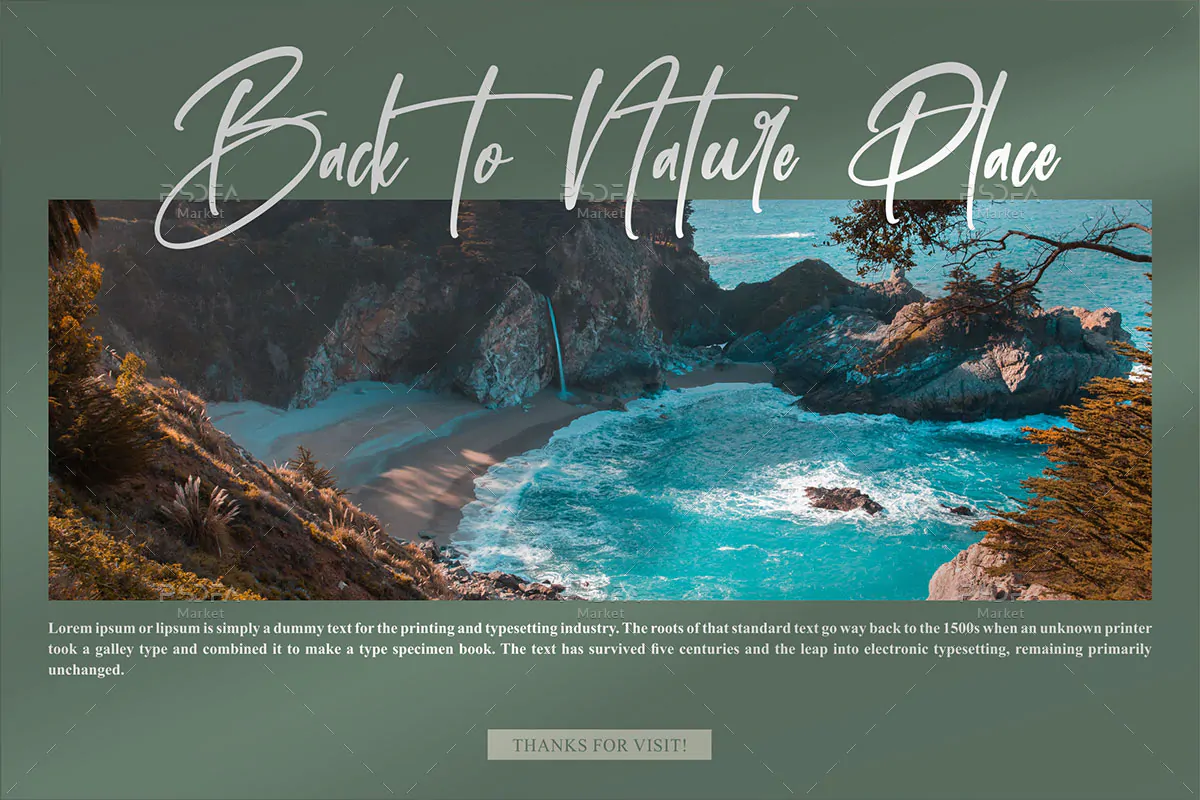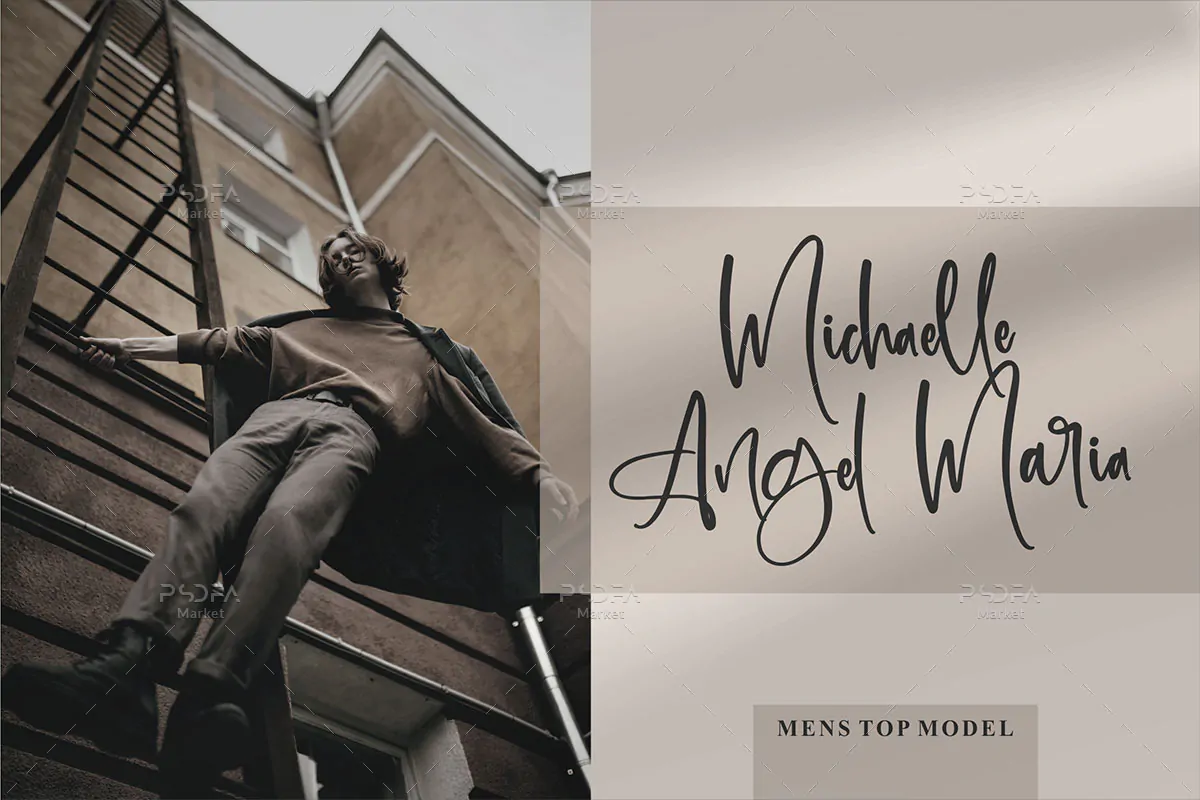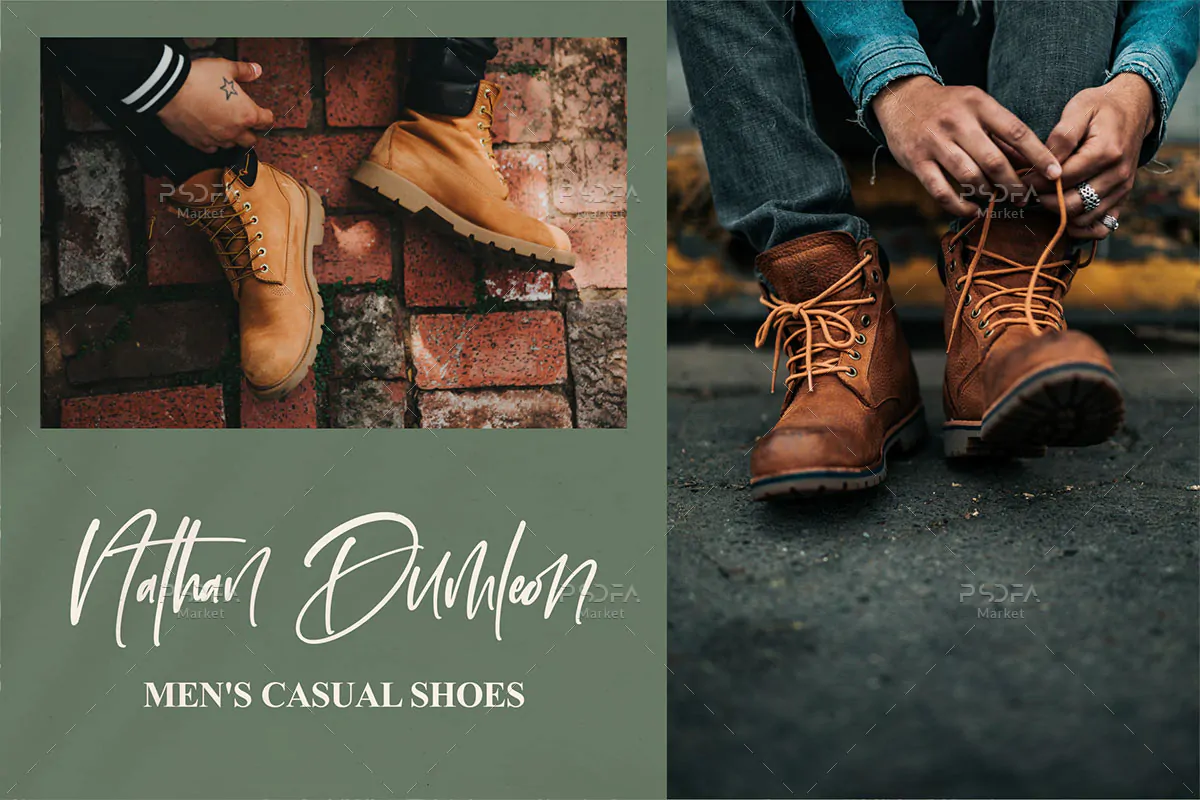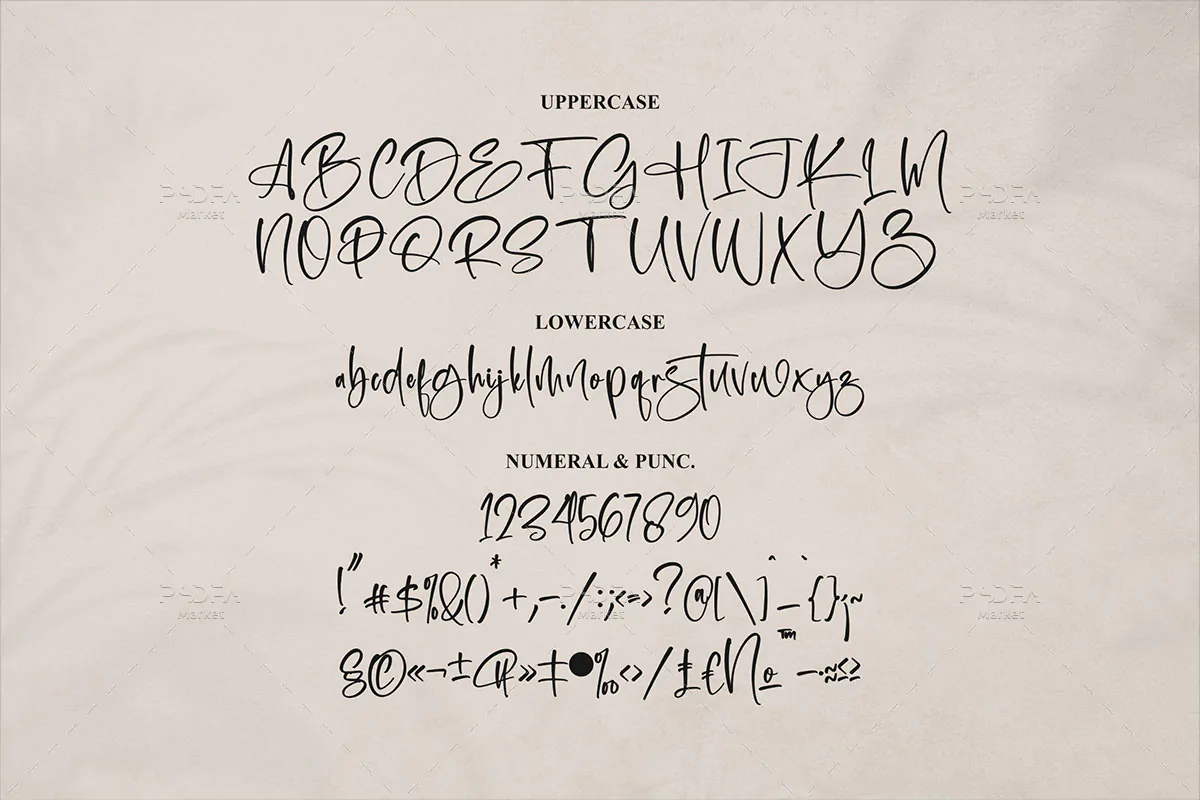
فونت دستنویس زیبا و یونیک Puertariko
فونت دستنویس زیبا و یونیک
فونت دستنویس زیبا و یونیک Puertariko یک قلم انگلیسی فوق العاده است که میتوانید از آن در طرح و پروژههای گرافیکی مختلف استفاده کنید. این فونت زیبا با وزن معمولی طراحی شده است که مناسب جهت استفاده در طراحی انواع کارت تبریک، کارت پستال، پست و استوری رسانههای اجتماعی، بسته بندی محصولات، طرحهای رمانتیک و عاشقانه، کارت ویزیت، بنر، پوستر و … میباشد.